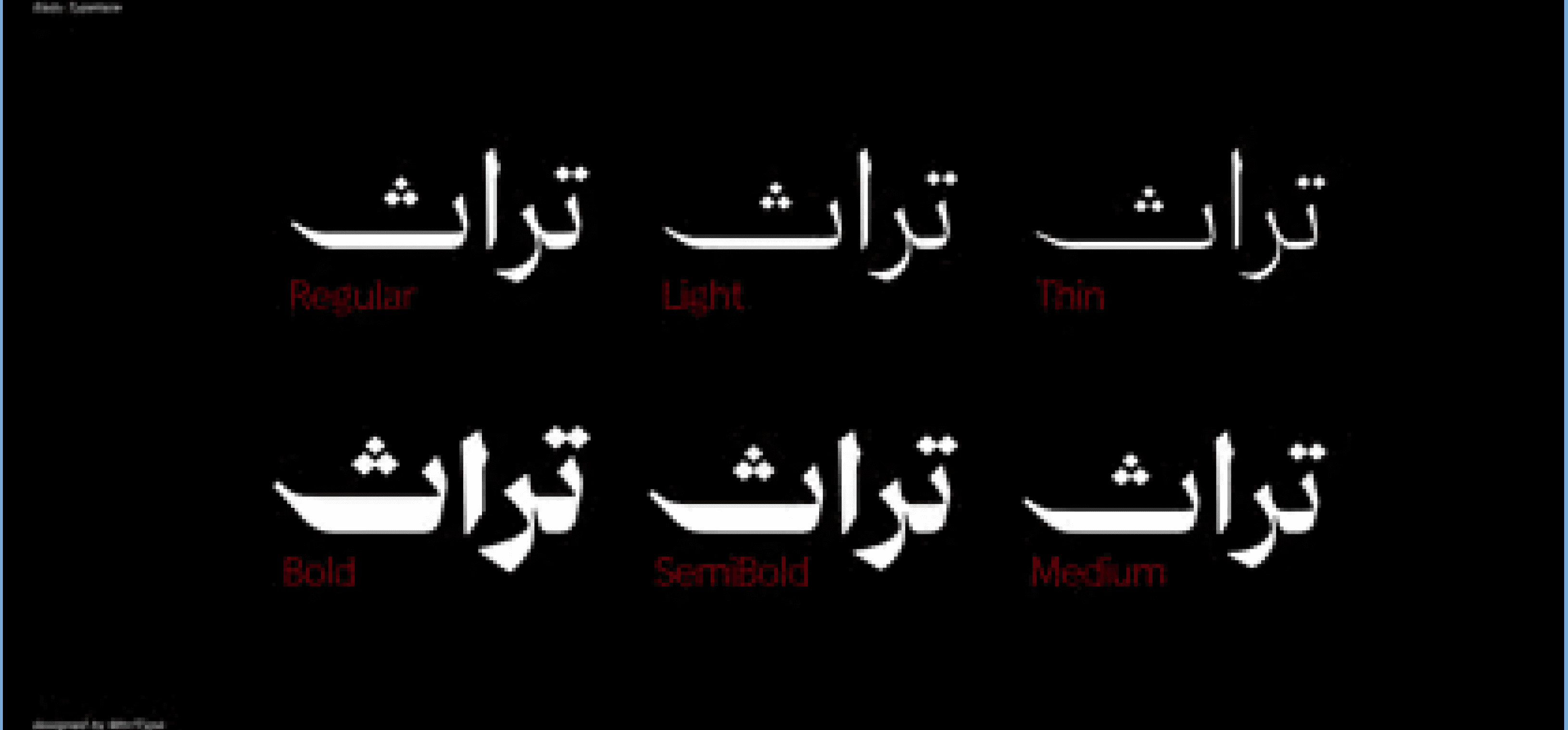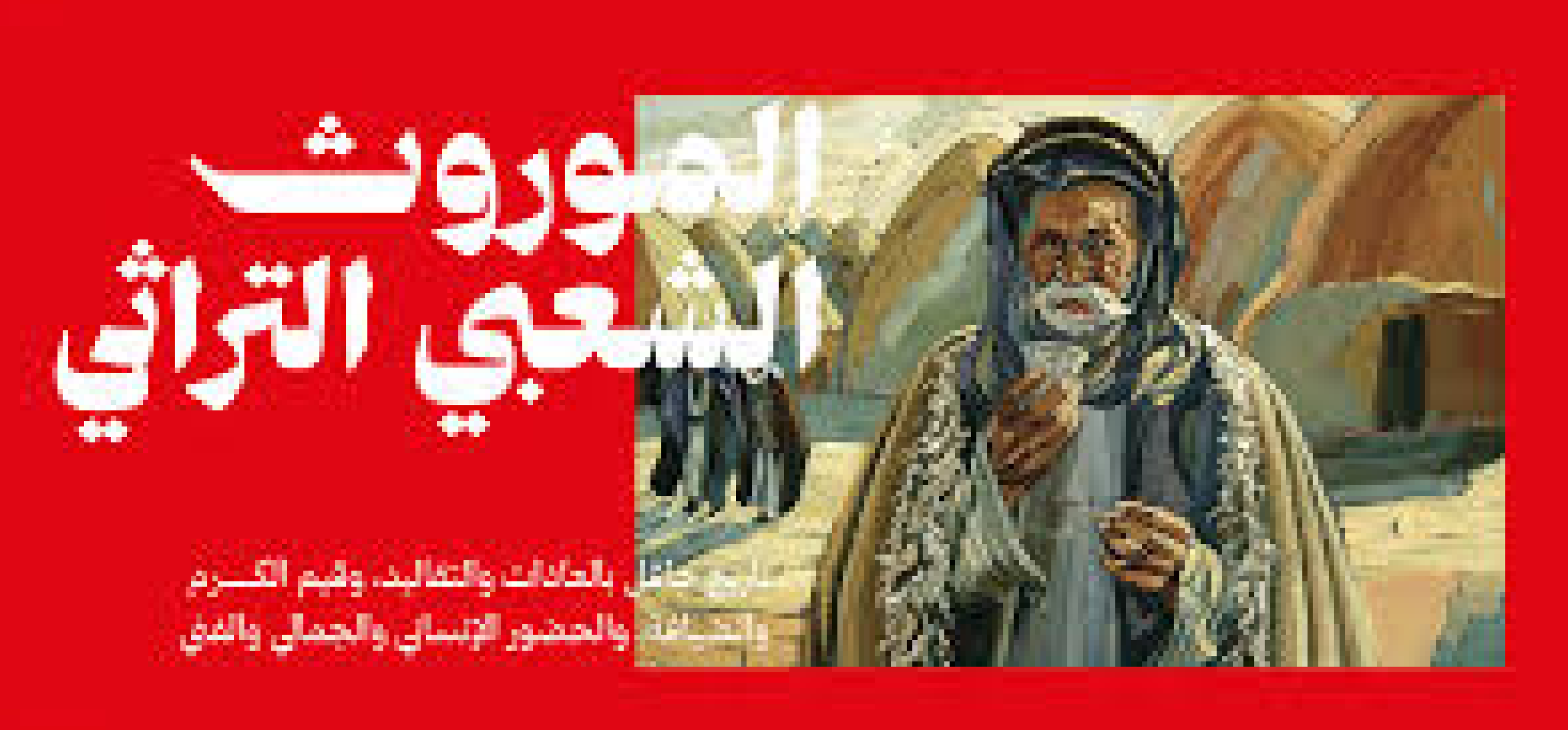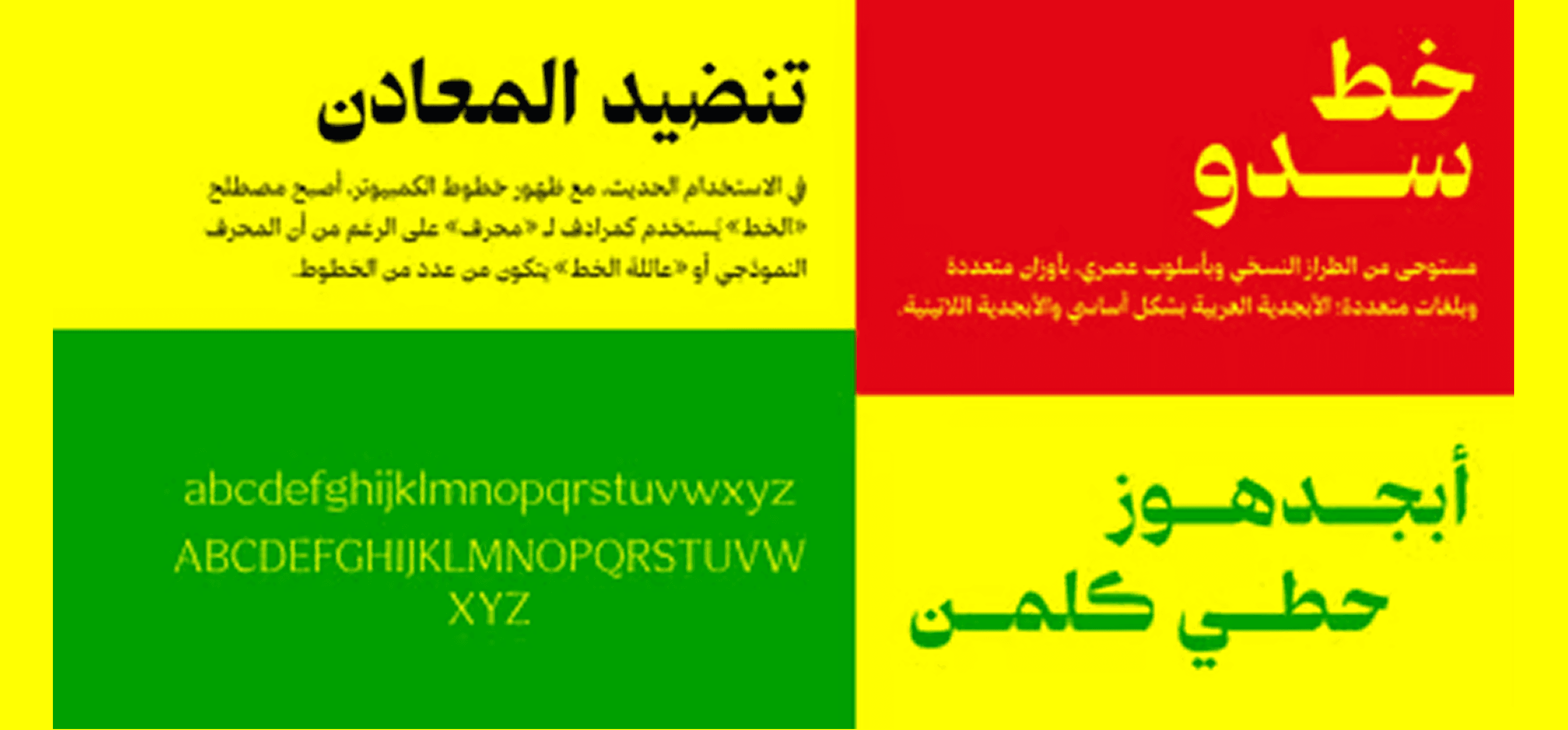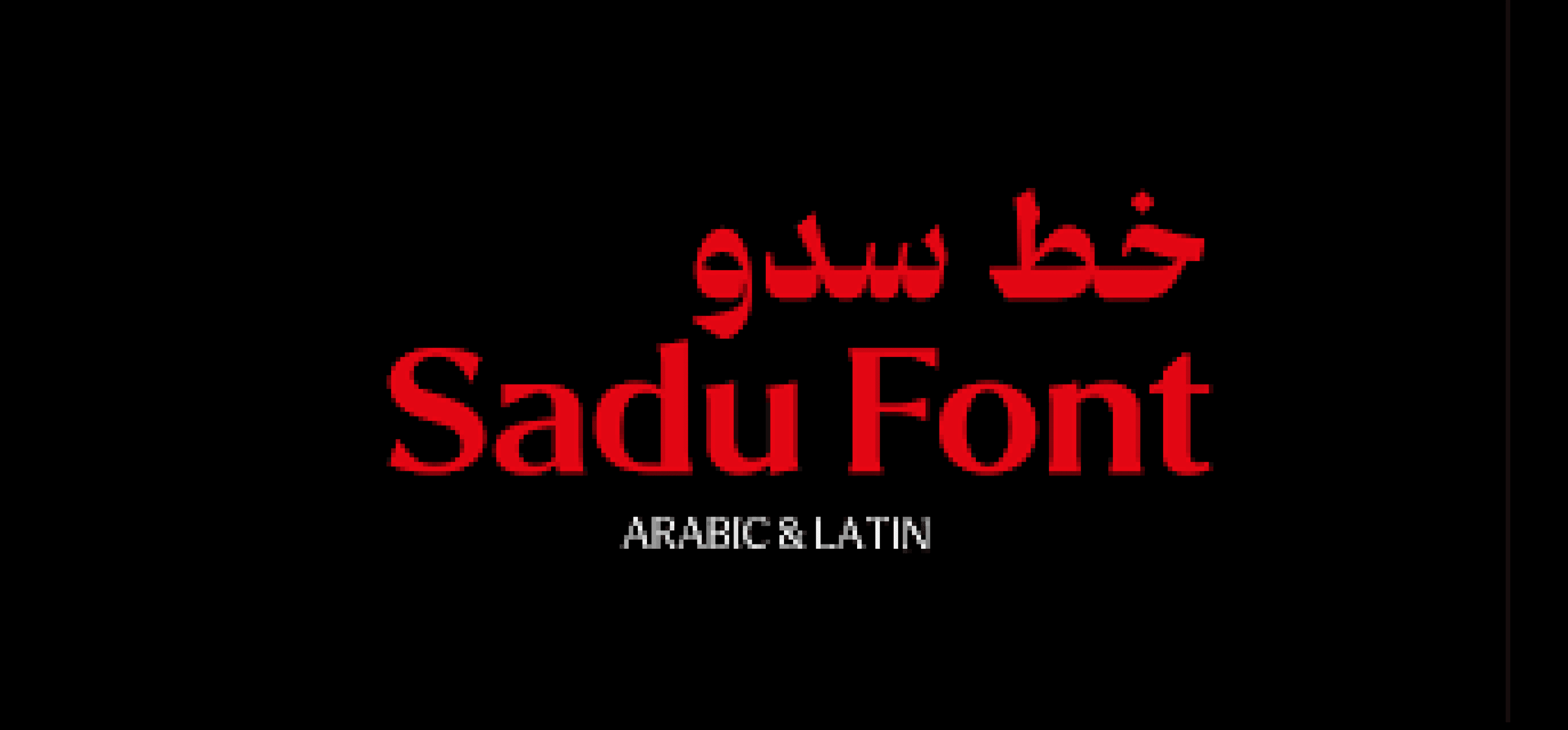
سادو هو خط تقليدي بلمسة عصرية يوفّر تجربة بصرية جذابة بحق. يتكوّن من عائلة تضم 6 أوزان، ويدعم اللغات التي تستخدم الحرف العربي مثل الفارسية والأردية، بالإضافة إلى الأبجدية اللاتينية.